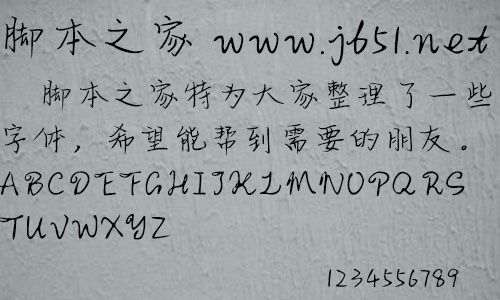
Aa貓主子咪咪一款不錯(cuò)的的藝術(shù)字體,由Aa字庫(kù)出品,字體筆觸纖細(xì),字形流暢,具有很好的視覺(jué)感,適合應(yīng)用于藝術(shù)設(shè)計(jì)、平面宣傳設(shè)計(jì)、網(wǎng)頁(yè)設(shè)計(jì),書(shū)法字帖等領(lǐng)域,需要的朋友可以前來(lái)本站下載。